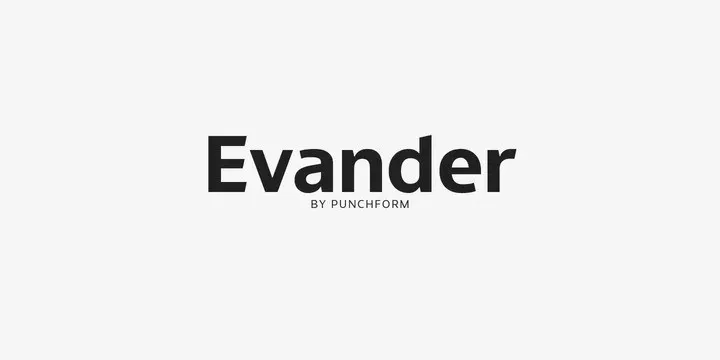
Evander Sans Serif é uma fonte moderna e geométrica inspirada na linguagem visual de design técnico e industrial. Seu design está influenciado pelas linhas retas e minimalistas dos caracteres sem serif, mas também incorpora um toque de sofisticação que faz dela uma opção ideal para projetos de design gráfico variados. Desenvolvida pelo designer Mihai Sorin da Punchform em 2020 como parte de sua família de fontes de sans-serif humanista, Evander traz consigo uma atmosfera neutral e moderna que se ajusta perfeitamente para textos legíveis, gráficos profissionais e design editorial. Suas linhas claras e retas a tornam ideal para o uso em variados estilos de design como branding, infográficos, sites ou material impresso. Evander Sans Serif é uma escolha sólida que traz à sua próxima criação gráfica um toque de elegância contemporânea.